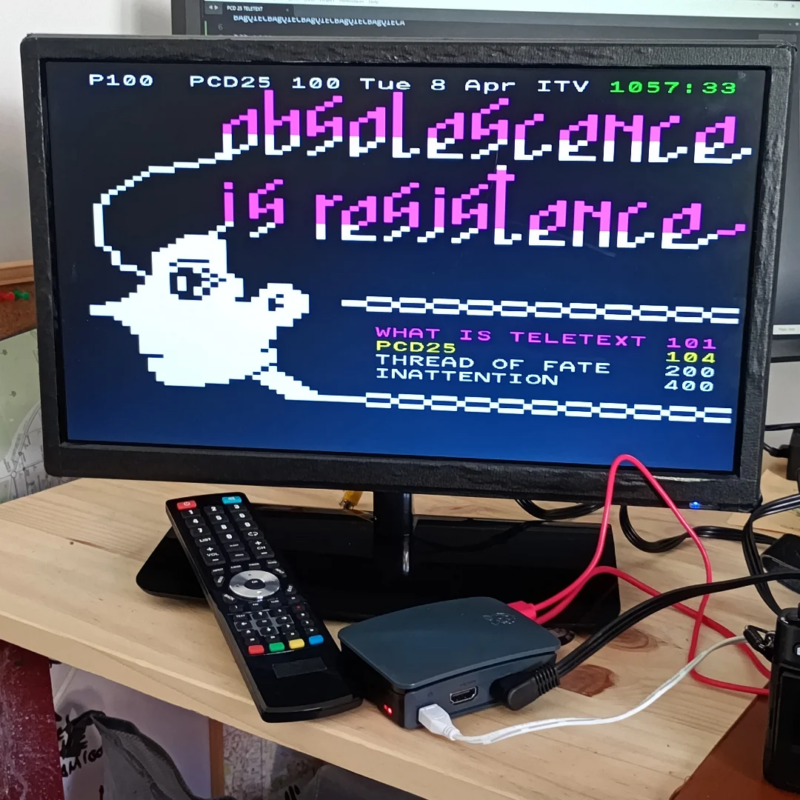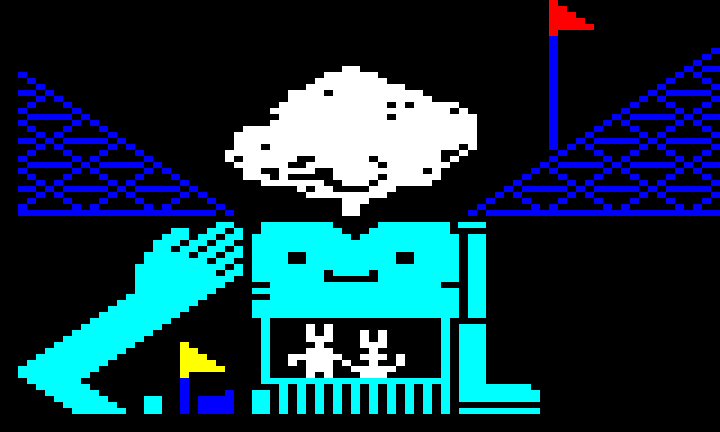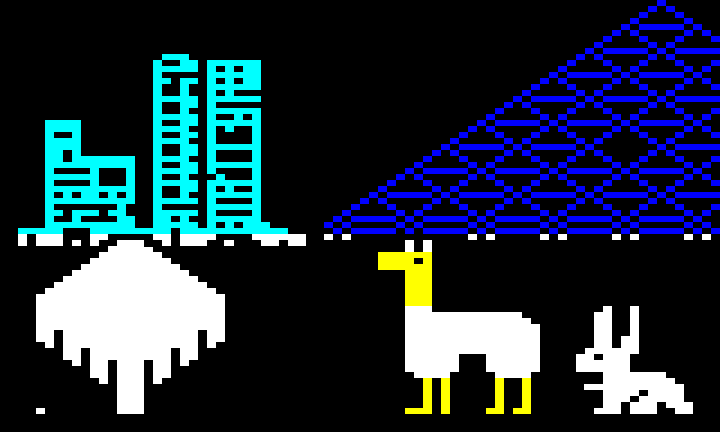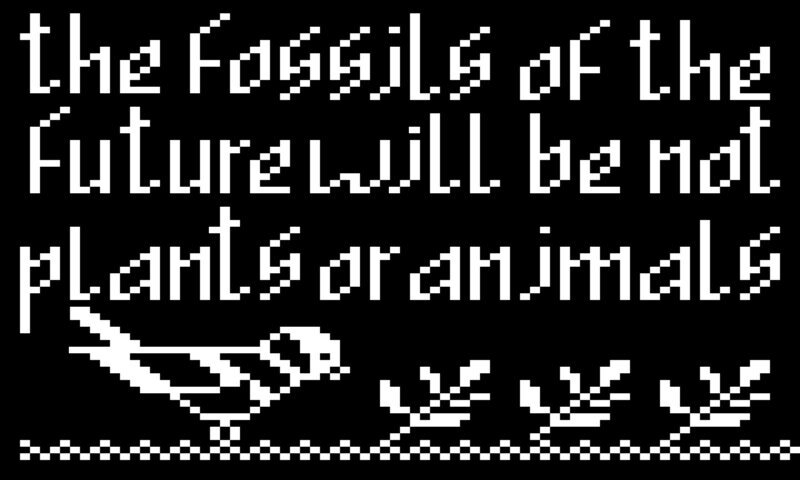
Raquel Meyers
Obsolescence is Resistance
Raquel Meyers arbeitet mit veralteten Technologien wie dem Commodore 64, Teletext, Schreibmaschinen oder Faxgeräten, kombiniert mit Fotografie, Animation und Stickerei sowie anderen Techniken. Sie definiert ihre Praxis als KYBDslöjd [mecanografía expandida], was grob übersetzt als „manuelle Fertigkeit mit einer Tastatur” bezeichnet werden kann. Diese basiert und bezieht sich auf die Schreibmaschine, konkrete Poesie, Demoszene und Brutalismus. Die Tastenanschläge und die Poesie tragen zu einem System bei, indem sie die Architektur von PETSCII, dem rohen und schmucklosen Zeichensatz von Commodore 64 und Teletext, offenbaren.